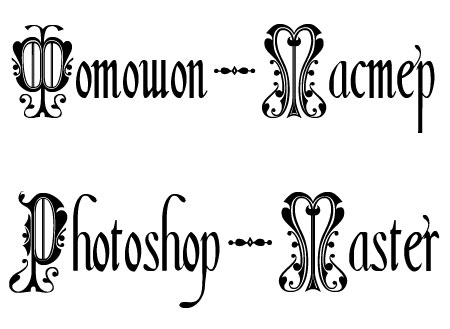
Очень красиво, спасибо!
Спасибо! Забавный шрифт.
шикарный шрифт!!!!!!!!!!!!!
Восхитительно!!!
Очень красиво!
Красота! Спасибо огромное!
Очень миленький ))
Прям в стиле модерн!) Классно!))
буква Ф на филина похожа)))